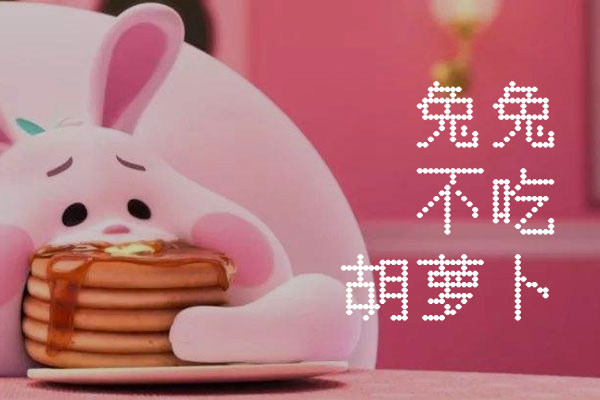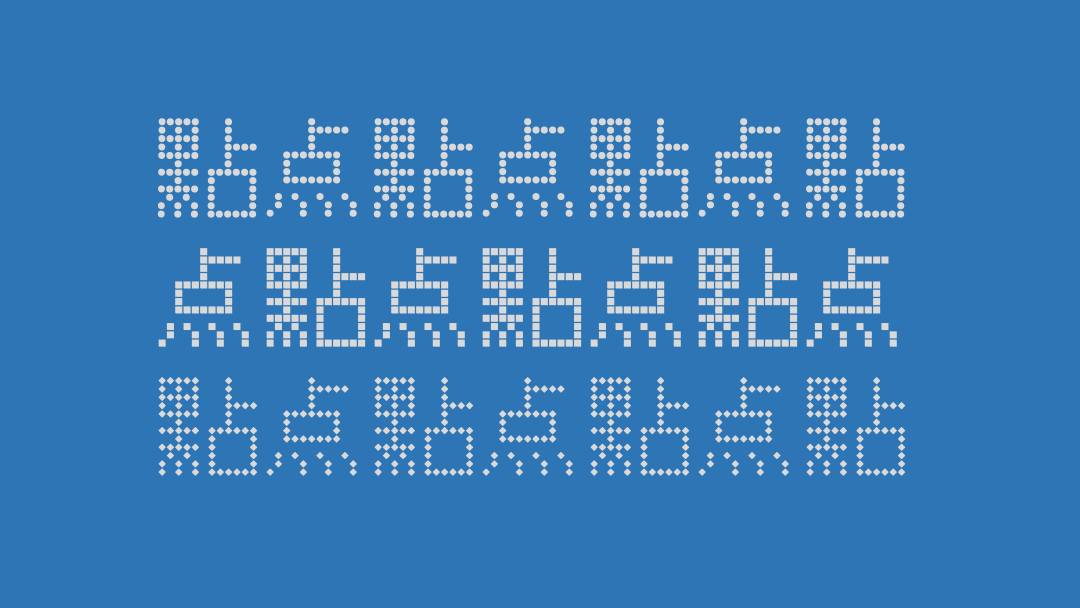
点点像素字体
点点像素字体(Dotted Songti)是一款引人注目的中文像素艺术字体,可在Github上免费获取其开源版本。该字体基于GPL 2.0协议发布,代表着中国大陆设计师wixette的精湛技艺和创意。
这款字体独具特色,包含了三种字型——圆点、方点与菱形点,每种字型均支持超过22000个Unicode字形,全面覆盖GBK编码中的简繁体汉字。字体文件包中包含三个文件,分别对应不同的字型,呈现出独特的视觉效果。
点点像素字体的创作灵感源自文泉驿项目的一种点阵字体。在经历矢量化处理、变形与美化之后,文泉驿点阵宋体被重塑为具有不同风格的点点像素字体。
无论是与现代还是复古设计风格搭配,点点像素字体都能在视觉上展现出其独特魅力。其灵活多变的字型能够满足各种设计需求,无论是标题、正文还是装饰性文字,都能在不同的屏幕或打印输出中呈现出色的表现效果。
总之,点点像素字体(Dotted Songti)是一款功能强大的中文像素艺术字体,具有独特的视觉效果和广泛的应用领域。其免费开源的特点更是为设计师们提供了很好的创作资源,成为了许多作品中的亮点。
点点像素字体效果预览
点点像素字体字体效果预览